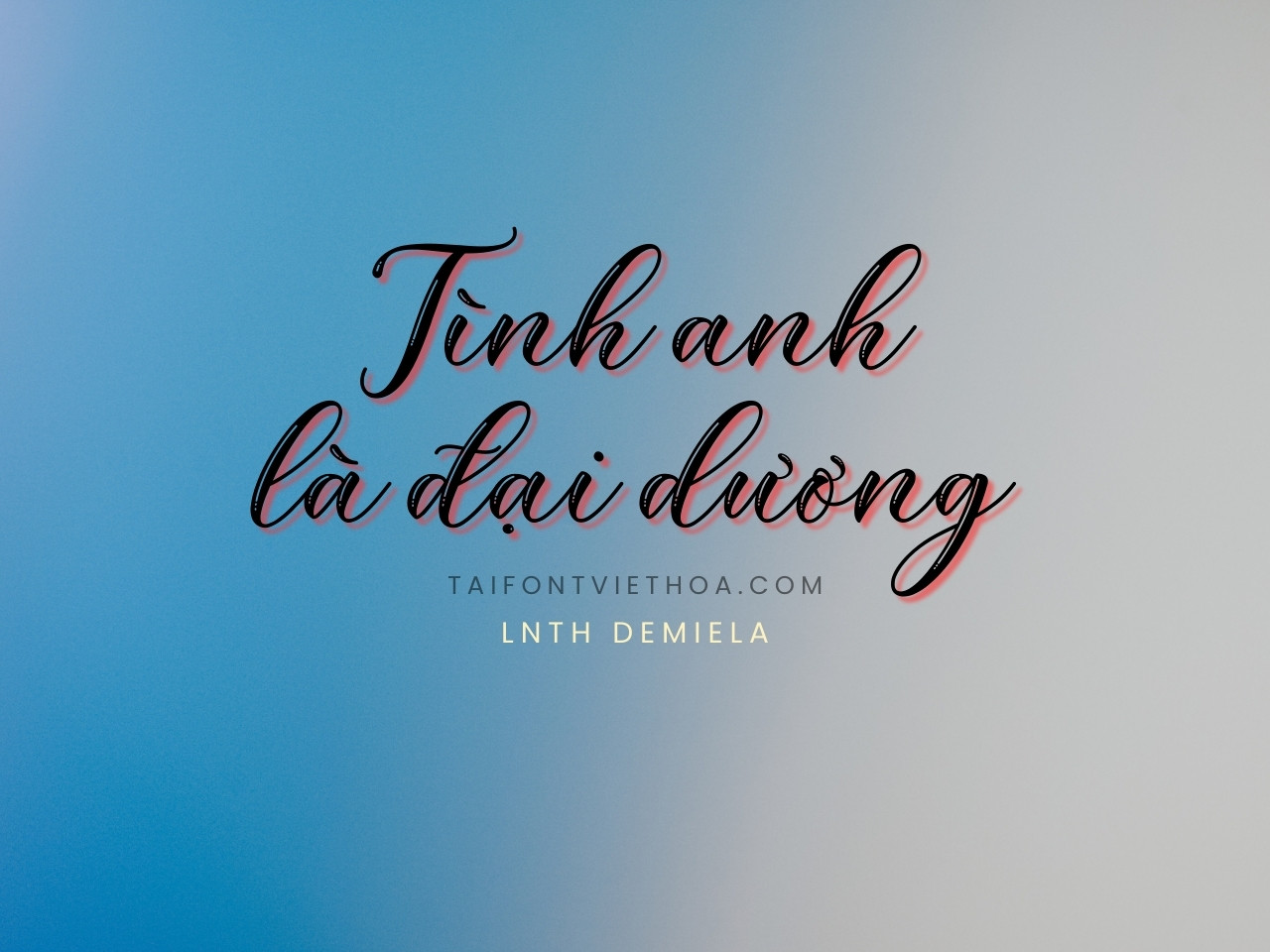
Font việt hóa LNTH Demiela
Tác giả Font: Jamalodin
Giới thiệu về font Demiela
Demiela là một kiểu chữ hiện đại thuộc nhóm font chữ ký (signature script), được thiết kế bởi nhà thiết kế Jamalodin. Font mang đến cảm giác mềm mại, tự nhiên và có phần cá tính nhờ những đường cong uyển chuyển cùng độ nghiêng nhẹ đặc trưng. Demiela được phát hành lần đầu trên các nền tảng font quốc tế như Creative Fabrica và FontBundles. Phiên bản Việt hóa được thực hiện bởi Tuỳn Pucca, bổ sung đầy đủ dấu tiếng Việt và hỗ trợ hơn 80 ngôn ngữ khác, phù hợp với người dùng ở nhiều khu vực khác nhau.
Đặc điểm thiết kế và ứng dụng của font Demiela
Demiela sở hữu các đường nét uyển chuyển, mô phỏng chữ viết tay bằng mực, kết hợp độ nghiêng mềm mại và các liên kết chữ (ligatures) tinh tế. Các ký tự được thiết kế hài hòa giữa phần gốc và phần kéo dài, giúp tăng tính biểu cảm cho văn bản. Bảng chữ cái Latin và ký tự mở rộng đều được tinh chỉnh để hỗ trợ tốt tiếng Việt mà vẫn giữ được cá tính đặc trưng của font.
Nhờ tính thẩm mỹ cao và sự duyên dáng trong thiết kế, Demiela phù hợp để ứng dụng trong các ngành nghề như: thiết kế logo cá nhân, thương hiệu mỹ phẩm, thời trang, spa, thiệp cưới, ấn phẩm sáng tạo hoặc typography nghệ thuật. Đây cũng là lựa chọn lý tưởng cho các dự án branding đề cao tính thủ công và sự thân thiện với người dùng.